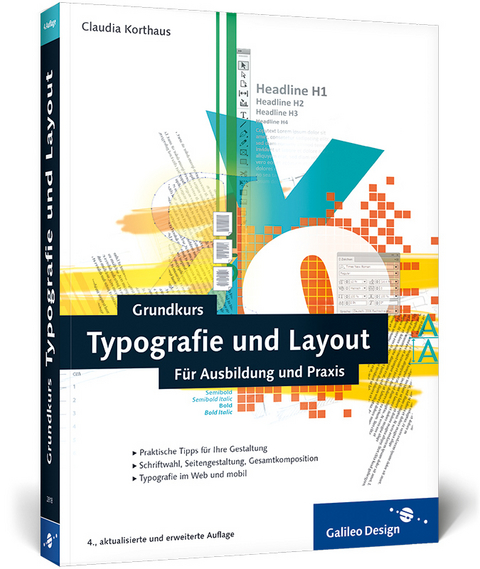
Grundkurs Typografie und Layout
- Praktische Tipps für Ihre Gestaltung
- Schriftwahl, Seitengestaltung, Gesamtkomposition
- Typografie im Web und mobil
Typografie und Layoutgestaltung - wer ist bei diesem Thema nicht froh, stets ein verlässliches Nachschlagewerk zur Hand zu haben. Wie war das noch einmal mit der Spationierung? Welcher Abstand kommt zwischen »z.B.«? Welche Schrift passt auf meinen Flyer, und woran erkenne ich das? Welche Möglichkeiten bieten aktuelle Techniken für gute Webtypografie? All diese Fragen und weitere rund um Textausrichtung, Wort- und Zeilenabstand beantwortet die Autorin in der vierten Auflage ihres Bestsellers.
Im Layout-Teil geht es um Gestaltungselemente wie Raum, Linien, Formen, aber auch konkret um Grundlinienraster, Seitenformate und Spalten. Claudia Korthaus gelingt es, Ihnen ein Gefühl für Gleichgewicht, Kontraste und Betonung zu vermitteln. Beispiele aus Print und Internet, umgesetzt mit QuarkXPress und InDesign, vervollständigen das Buch. Dieser praktische Begleiter beweist, dass Typografie Spaß macht und Ihre grafischen Werke verbessert, wenn man sie beherrscht - und genau das lernen Sie hier.
Entdecken Sie die Welt der Schrift!
Sie möchten einen tieferen Einblick in die kleinen und großen Geheimnisse einer gelungenen Gestaltung gewinnen? Claudia Korthaus nimmt Sie mit auf eine Reise in die Welt der Schrift und verrät Ihnen, wie Sie von einem leeren Blatt zu einer überzeugenden Seite gelangen.
Der praktische und verständliche Einstieg
Gute Typografie macht ein perfektes Schriftstück oder eine überzeugende Website aus! Diese liebevoll gestaltete Einführung zeigt, wie es geht – von der passenden Schriftwahl über Abstände bis hin zu Grundlinienrastern und den optimalen Seitenformaten.
Mit attraktiven Beispielen schulen Sie Ihren Blick
Ob Flyer, Visitenkarte oder Broschüre – erst durch den richtigen Einsatz von Schrift und das korrekte Zusammenspiel der Gestaltungselemente erzielen Sie die gewünschte Wirkung. Erfahren Sie hier, wie Sie Ihre Printdesigns so gestalten, dass sie gut ankommen!
Typografie im Web und mobil
Auch im Web oder mobil können Sie mit guter Typografie überzeugen: Welche Schriften eignen sich, wie erhöhen Sie die Lesbarkeit, wie groß sollte eine Schrift mindestens sein? Lesen Sie alles über die neuesten Entwicklungen rund um Schrift im Internet und auf Smartphones und Tablets.
Themen sind insbesondere:
- Basiswissen Schrift
- Geschichte der Schrift
- Wichtige Schriftkünstler
- Schriftwahl und Wirkung
- Buchstabe, Wort, Zeile
- Schnitte, Serifen, Ligaturen
- Größen und Abstände wählen
- Ausrichtung, Einzug, Umbruch
- Typo in InDesign und QuarkXPress
- Layouts gestalten
- Papierformat, Raumaufteilung
- Den Satzspiegel anlegen
- Text und Bild kombinieren
- Typografie im Web
- Typografie mobil
- Schreibregeln und Tipps
- Vorher-nachher-Beispiele
- Schrifttechnologien
... Vorwort ... 16
1 ... Basiswissen Schrift ... 17
1.1 ... Schriftentwicklung ... 18
... 3500 v. Chr. und die Sumerer ... 18
... 3000 v. Chr. und die Hieroglyphen ... 19
... 1200 v. Chr. und die Phönizier ... 20
... 800 v. Chr. und die Griechen ... 21
... 100 v. Chr. und die Römische Kapitalis ... 22
... 800 und die Karolingische Minuskel ... 24
... 1000 und die Romanik ... 25
... 1200 und die hochgestreckte Gotik ... 26
... 1400 und der Beginn der Renaissance ... 27
... 1450 und Gutenberg ... 28
... 1500, die gebrochenen Schriften und die Französische Renaissance-Antiqua ... 29
... 1500 und die Kursive ... 30
... 1700 und Barock und Rokoko ... 31
... 1800 und der Klassizismus ... 32
... 1880 und der Jugendstil ... 34
... 1900, die Times und die serifenlosen Schriften ... 35
... 1920 und das Bauhaus ... 36
... 1950 und die Schweizer Typografie ... 38
... 70er, 80er, 90er und die Einführung des DTP ... 38
... 1990 bis heute ... 41
... Pixel- und Screenfonts ... 41
1.2 ... Schriftschnitt und Schriftfamilien ... 42
... Ist Italic eine Kursive? ... 42
... Frutiger und seine Zahlen ... 43
... MultipleMaster ... 44
... Schrift als Gebrauchsinstrument ... 45
... Schriftenwelle in der Industrialisierung ... 45
... Experten ... 46
... Kapitälchen ... 46
... Falsche Kapitälchen – ein Kapitalverbrechen? ... 47